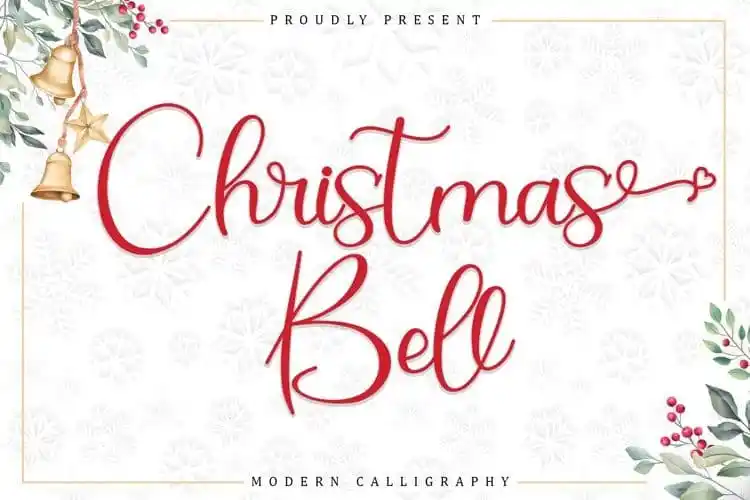
Christmas Bell Calligraphy Font – Download Grátis
A fonte de escrita “Christmas Bell Calligraphy Font” é uma obra-prima que transmite elegância através da tipografia moderna. Desenvolvida pela Sakha Design, esta fonte mantém os tradicionais elementos estilizados do calligrafismo enquanto se atualiza e permanece fresca e contemporânea. Ela é perfeita para criar mensagens encantadoras que destacam seu trabalho ou marca, além de ser perfeita para aplicativos diversos como fotografias, cartões de agradecimento, posteres, cartões de convite para casamentos, roupas, etiquetas e materiais de escrita. Com “Christmas Bell”, você pode explorar infinitamente as possibilidades criativas que essa fonte oferece. Ideal tanto para personalizar sua própria arte quanto para adaptar a um design já existente, esta font é uma opção perfeita para qualquer projeto onde o estilo e a qualidade são cruciais.